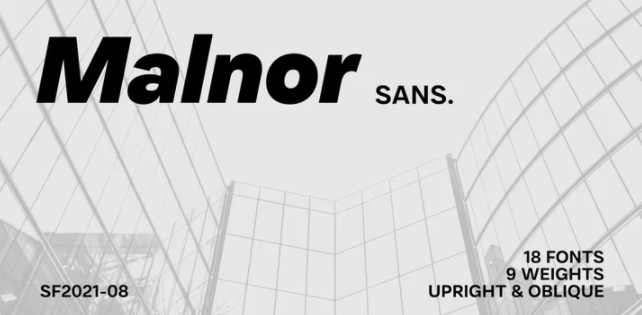
Malnor Sans - это нормальное семейство шрифтов sans serif, состоящее из 18 шрифтов. В современном стиле или нео-гротеске Malnor sans имеет сбалансированные пропорции в каждой букве, он чистый, минимальный и холодный. Есть несколько альтернативных букв, которые можно использовать как в вертикальном, так и в наклонном стиле. Одноэтажная буква "a" может создать более геометрическое впечатление, хотя она и не является чисто геометрической. Есть также альтернативная двухэтажная "a" с хвостиком, двухэтажная "g" и альтернативная "l", которые можно использовать вместе с помощью функций "соль" или "стилистические наборы" для создания более теплой атмосферы.
Malnor Sans в настоящее время содержит около 900 глифов, включая диакритические знаки, которые поддерживают широкий латинский язык.